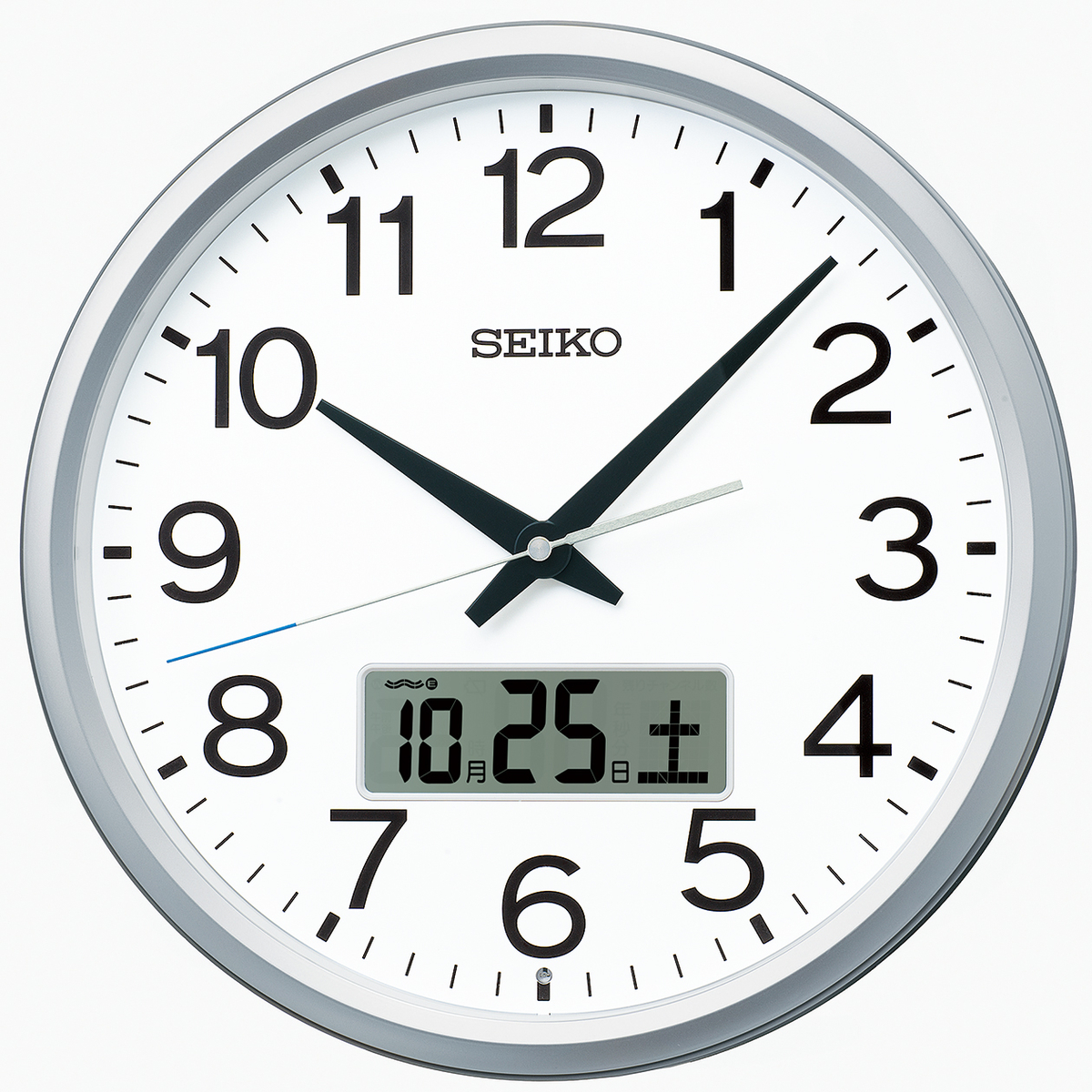
1日最大32回の任意の設定時刻をチャイムでお知らせできるユニバーサルデザインフォント使用のセイコークロックの掛時計「PT202S」
PT202Sの特長2「判読性抜群のユニバーサルデザインフォント(UDフォント)」
ユニバーサルデザインフォント(UDフォント)とは、文化や言語、国籍、年齢、性別、能力などの違いにかかわらずにできるだけ多くの人が利用できるコンセプトであるユニバーサルデザイン(UD)をもとに設計されたフォント(書体)。
フォントワークスと共同開発したユニバーサルデザインフォント(UDフォント)を使用。一瞬での判読が求められる掛時計としての時刻の見易さを徹底的に追求した。
▼「3」の口のアキを広く設計
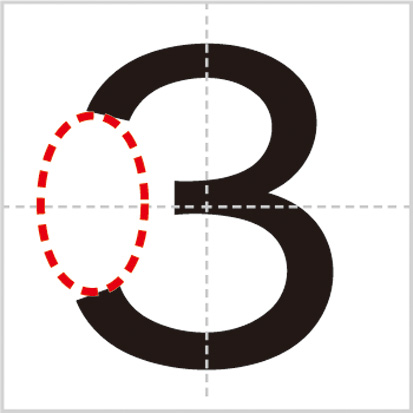
▼「6」と「9」の線の始まりと終わりを斜めにカット